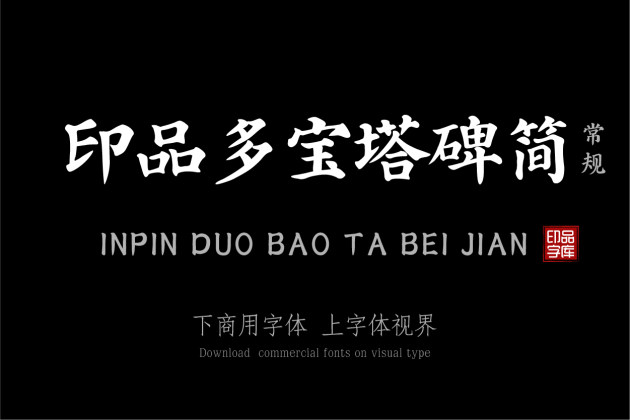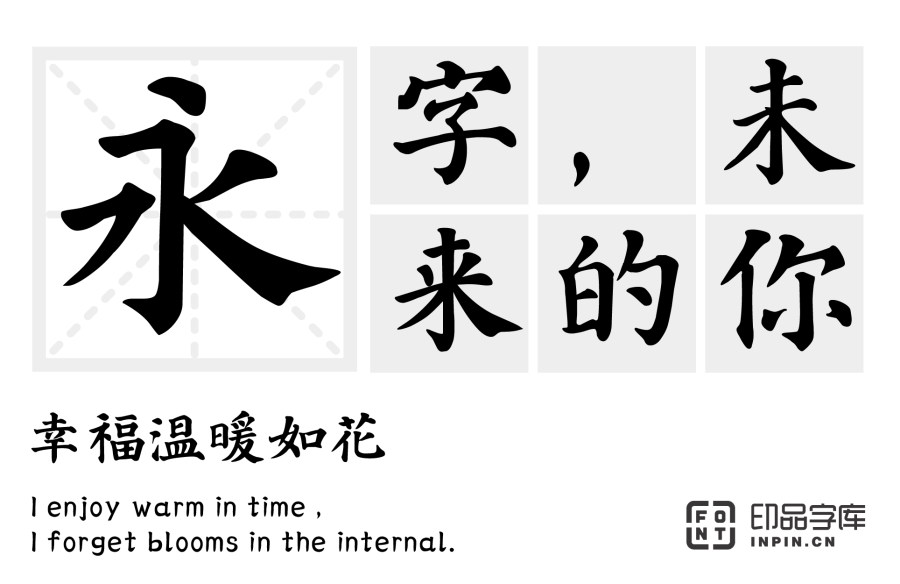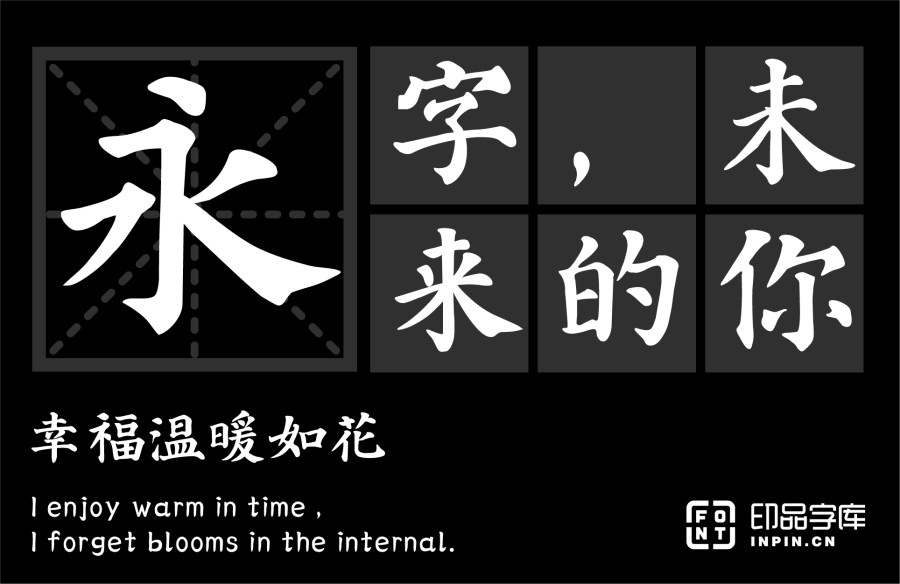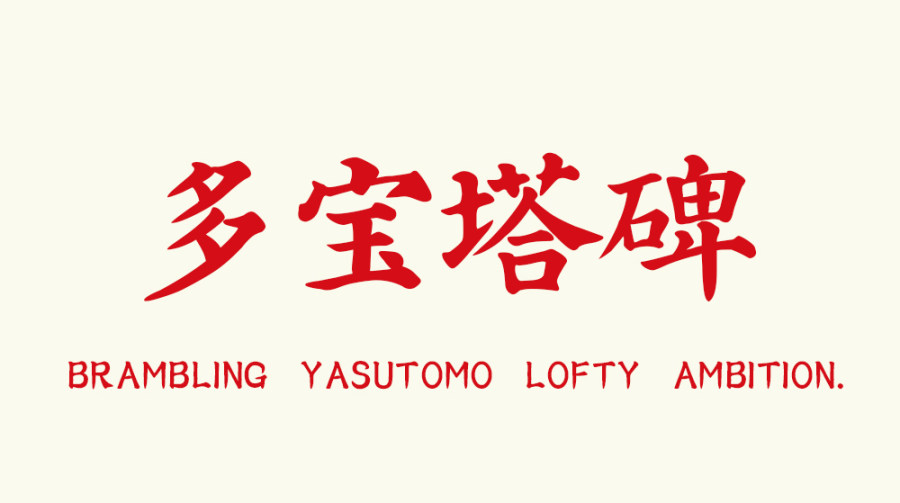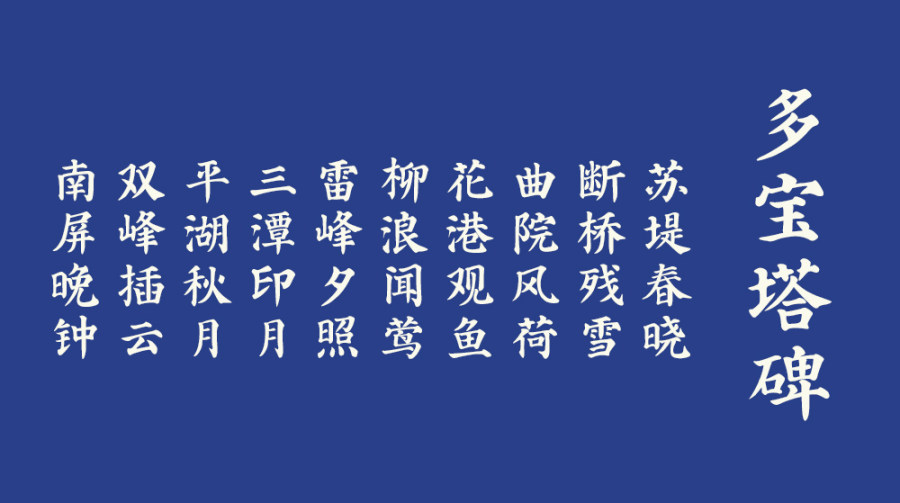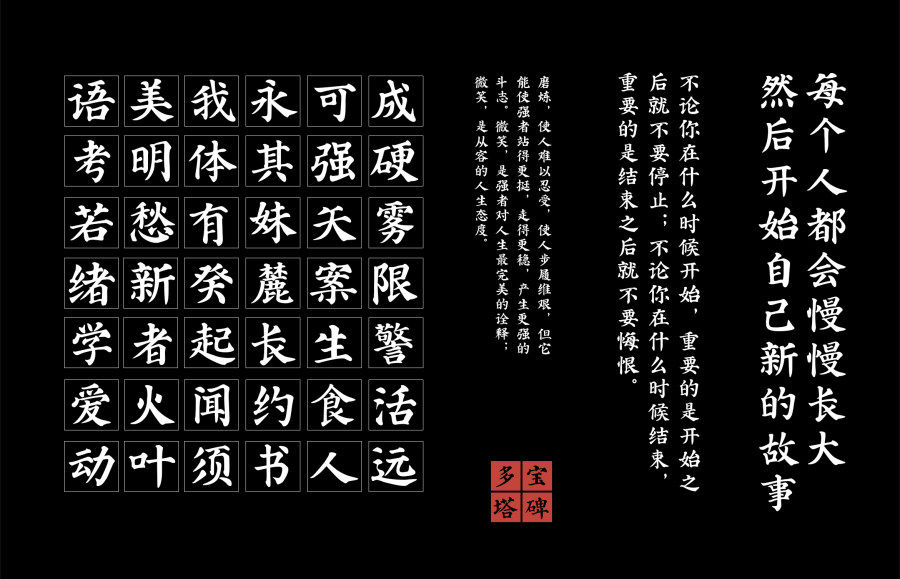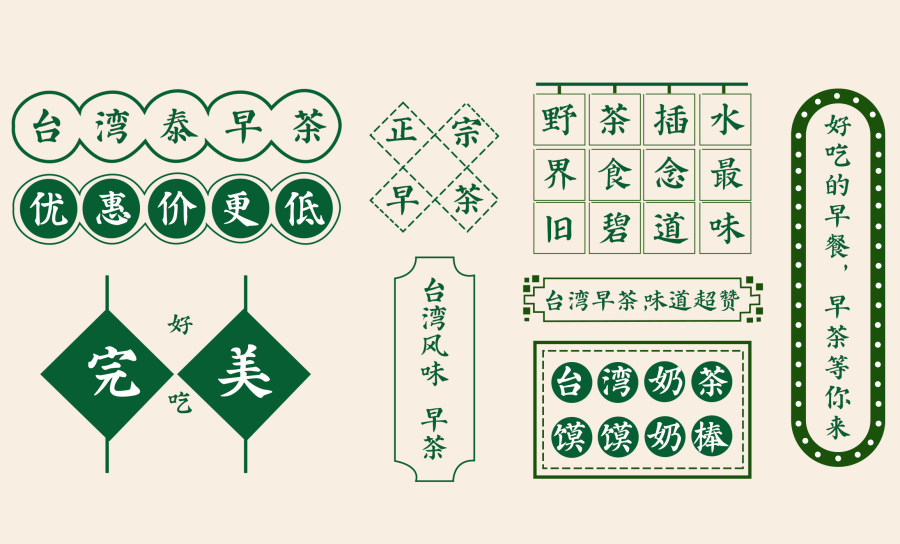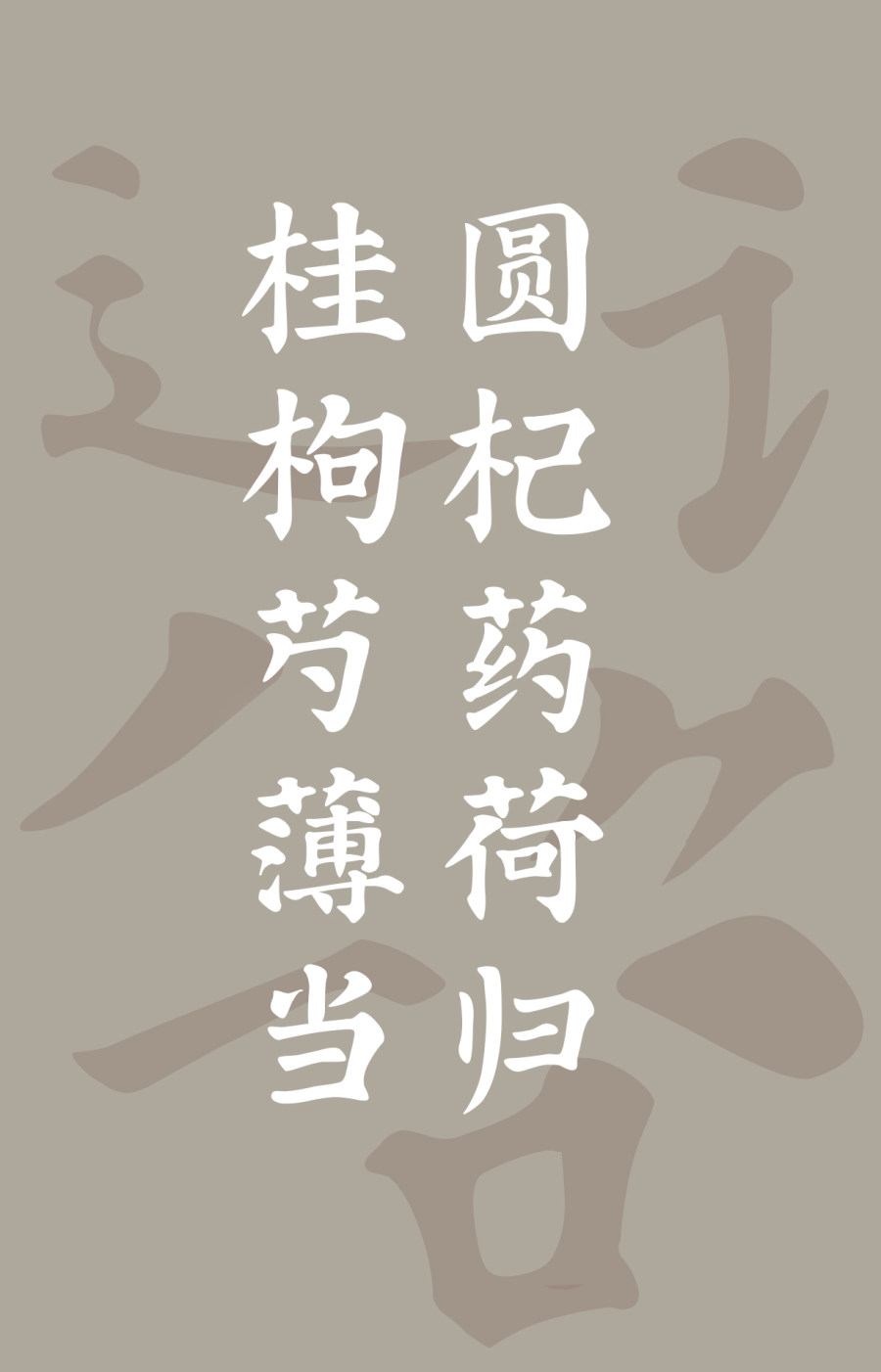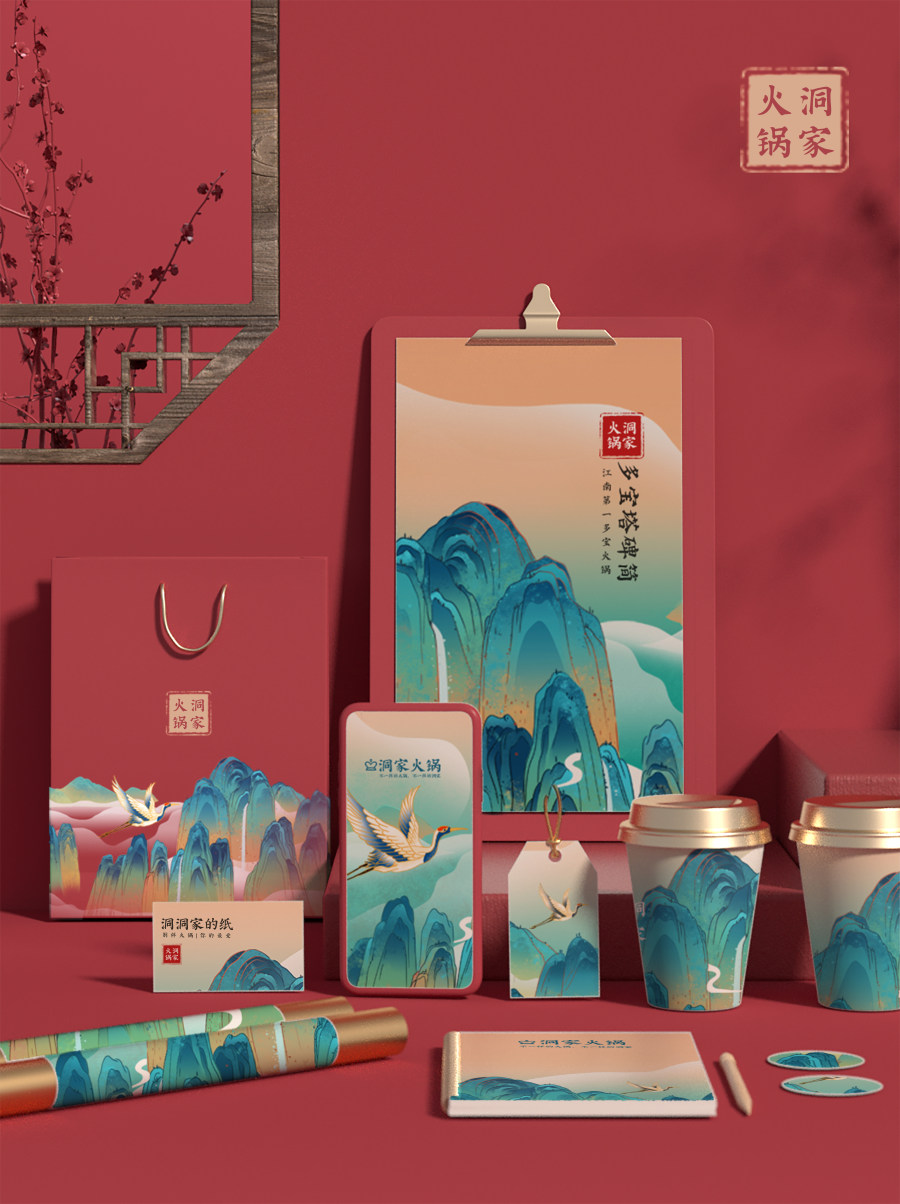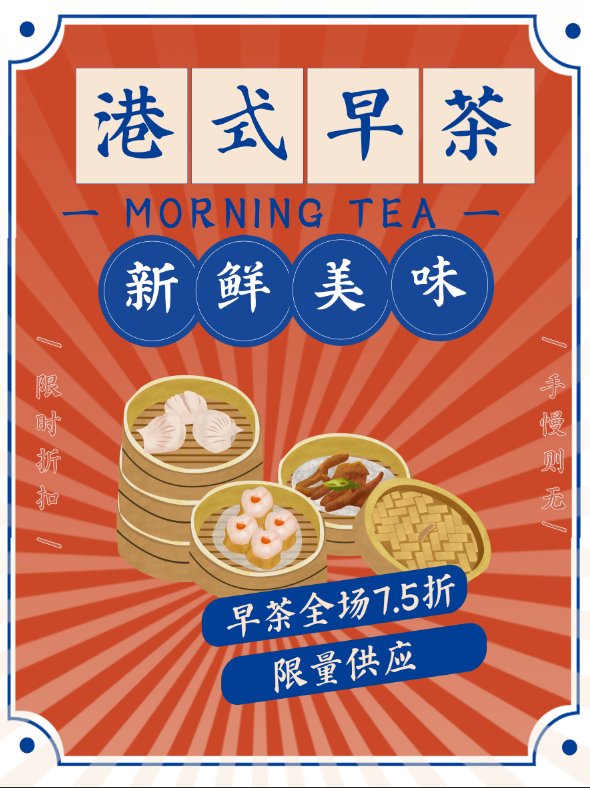
《印品多宝塔碑简》是参考唐代书法家颜真卿的《多宝塔碑》制作的楷体。使其既保留了颜公笔法风骨精髓,又便于现代人阅读使用。撇画较轻盈挺健,捺画却粗壮有力,字型稍方,端庄平稳。分享到
《印品多宝塔碑简》字体故事 《印品多宝塔碑简》制作源于唐代书法家颜真卿的《多宝塔碑》,全称《大唐西京千福寺多宝佛塔感应碑》,该碑字是颜真卿“颜体”楷书的初步形成阶段的代表作之一。 在做这款字之前,设计师查阅了大量的关于多宝塔碑图文史载,在一定的了解后总结得出:多宝塔碑用笔多用中锋,起笔和收笔有明显的顿按,竖画粗壮,横、竖笔画粗细对比鲜明,撇画较轻盈挺健,捺画却粗壮有力,字型稍方,端庄平稳。在保持这些基本特征不变并不影响辨识度的情况下,我将碑字中的传统笔画特色与现今简体字笔画结构结合,使其既保留了颜公笔法风骨精髓,又便于现代人阅读使用。后增添符号设计,完成简体7753字符集。 设计师感受:制作完成这款《印品多宝塔碑简》在提升我本身对字体的了解的同时也使我深刻感受到颜公书法之精妙,字体作为中国传统文化瑰宝之厚重。所以在成就自己的同时更希望这是一次对颜真卿书法的致敬与发展,中国传统字体的传承与发扬。